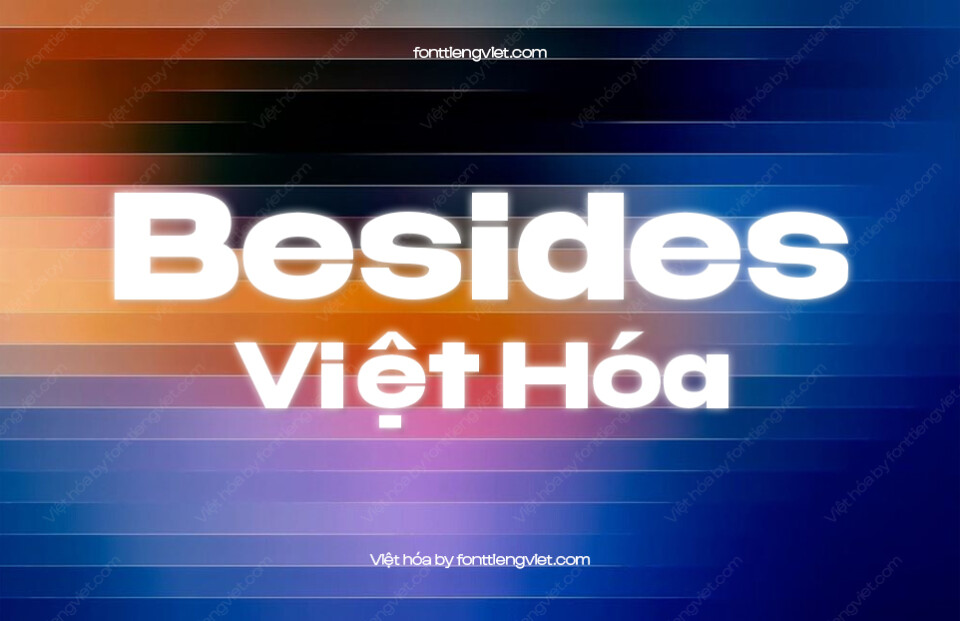
Font Việt hóa 1FTV VIP Besides
Trong thế giới thiết kế đồ họa hiện đại, việc lựa chọn một bộ phông chữ phù hợp đóng vai trò quyết định đến sự thành công của một tác phẩm nghệ thuật. Font Việt hóa 1FTV VIP Besides nổi lên như một lựa chọn hàng đầu cho những ai đang tìm kiếm sự kết hợp hoàn hảo giữa nét cổ điển và hơi thở đương đại. Đối với những người mới bắt đầu hoặc các bạn học sinh đang tìm tòi về sáng tạo nội dung, việc sở hữu một Font Miễn Phí chất lượng như thế này sẽ giúp bài thuyết trình hay bìa báo tường trở nên chuyên nghiệp hơn bao giờ hết. Bộ font này không chỉ hỗ trợ đầy đủ tiếng Việt mà còn mang đến trải nghiệm thị giác mượt mà, giúp thông điệp truyền tải đến người xem một cách tự nhiên và thu hút nhất.
Đặc điểm nổi bật của Font Việt hóa 1FTV VIP Besides
Lý do khiến Font Việt hóa 1FTV VIP Besides nhận được sự yêu thích nồng nhiệt từ cộng đồng designer Việt Nam chính là sự chỉn chu trong từng nét chữ. Phông chữ này được thiết kế với độ tương phản vừa phải, giúp văn bản dễ đọc ngay cả ở kích thước nhỏ. Đặc biệt, các ký tự dấu tiếng Việt đã được tinh chỉnh tỉ mỉ để không bị lỗi chân hoặc nhảy dòng, tạo nên sự đồng nhất tuyệt đối cho văn bản. Đây là một yếu tố cực kỳ quan trọng đối với môi trường giáo dục, nơi mà sự chính xác về mặt hiển thị luôn được đặt lên hàng đầu.
Tính ứng dụng linh hoạt trong đời sống và học tập
Bạn có thể sử dụng bộ font này cho rất nhiều mục đích khác nhau. Trong học đường, nó cực kỳ phù hợp để làm tiêu đề cho các slide thuyết trình PowerPoint, giúp bài giảng của thầy cô và bài làm của học sinh trở nên sinh động hơn. Trong lĩnh vực truyền thông, đây là công cụ đắc lực để thiết kế poster sự kiện, thiệp chúc mừng hoặc các banner quảng cáo trên mạng xã hội. Sự thanh lịch của nó mang lại cảm giác tin cậy, đồng thời vẫn giữ được nét trẻ trung, năng động cần thiết cho những dự án sáng tạo của giới trẻ.
Cách tối ưu hóa thiết kế với Font Việt hóa 1FTV VIP Besides
Để tận dụng tối đa vẻ đẹp của Font Việt hóa 1FTV VIP Besides, người dùng nên chú ý đến cách phối hợp màu sắc và khoảng cách giữa các chữ cái. Việc kết hợp font này với những tông màu pastel nhẹ nhàng sẽ tạo ra phong cách tối giản, hiện đại. Ngược lại, nếu sử dụng trên các nền ảnh có độ tương phản cao, phông chữ sẽ tạo nên một điểm nhấn mạnh mẽ, giúp tiêu đề bài viết của bạn trở nên nổi bật ngay lập tức. Đừng ngần ngại thử nghiệm các kiểu định dạng như in đậm hoặc in nghiêng để tạo ra hệ thống phân cấp thông tin rõ ràng cho tài liệu của mình.
Lợi ích khi sử dụng font chữ chuẩn mã hóa